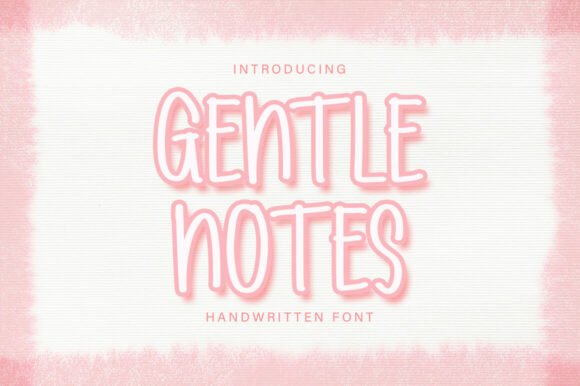
Gentle Notes
適切なデザイン要素を見つけるのは難しい場合がありますが、Gentle Notesは作品を即座に引き立てる優れたコレクションを提供します。
POD(オンデマンド印刷)製品、結婚式の招待状、またはソーシャルメディアのグラフィックを作成している場合でも、Gentle Notesは理想的です。